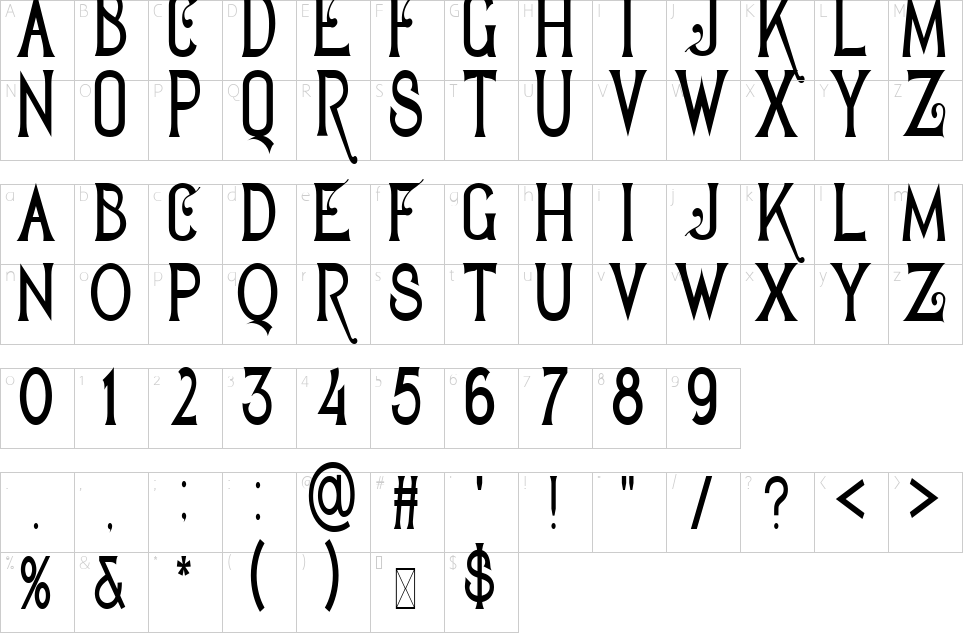
Geajer Font
A Geajer é uma elegante fonte que oferece uma experiência visual sofisticada para qualquer projeto digital. Desenvolvida pela 177Studio.com e já baixada mais de três mil vezes, essa fonte está disponível tanto para os sistemas Windows quanto Mac. Seja você um designer profissional ou iniciante, a Geajer traz com ela uma variedade de opções que podem adicionar estilo ao seu trabalho gráfico. Suas linhas leves e arredondadas complementam perfeitamente qualquer projeto, oferecendo tanto uma solução moderna quanto uma atmosfera mais tradicional. Ideal para seletor de cores, designers de logotipos ou até mesmo aqueles que simplesmente querem criar um texto com um ar diferenciado, a Geajer é um recurso gráfico valioso no seu kit de ferramentas digitais. Embarque nesta aventura de adicionar personalidade e sofisticação ao seu trabalho com a Geajer.
Mapa de caracteres da fonte Geajer Font